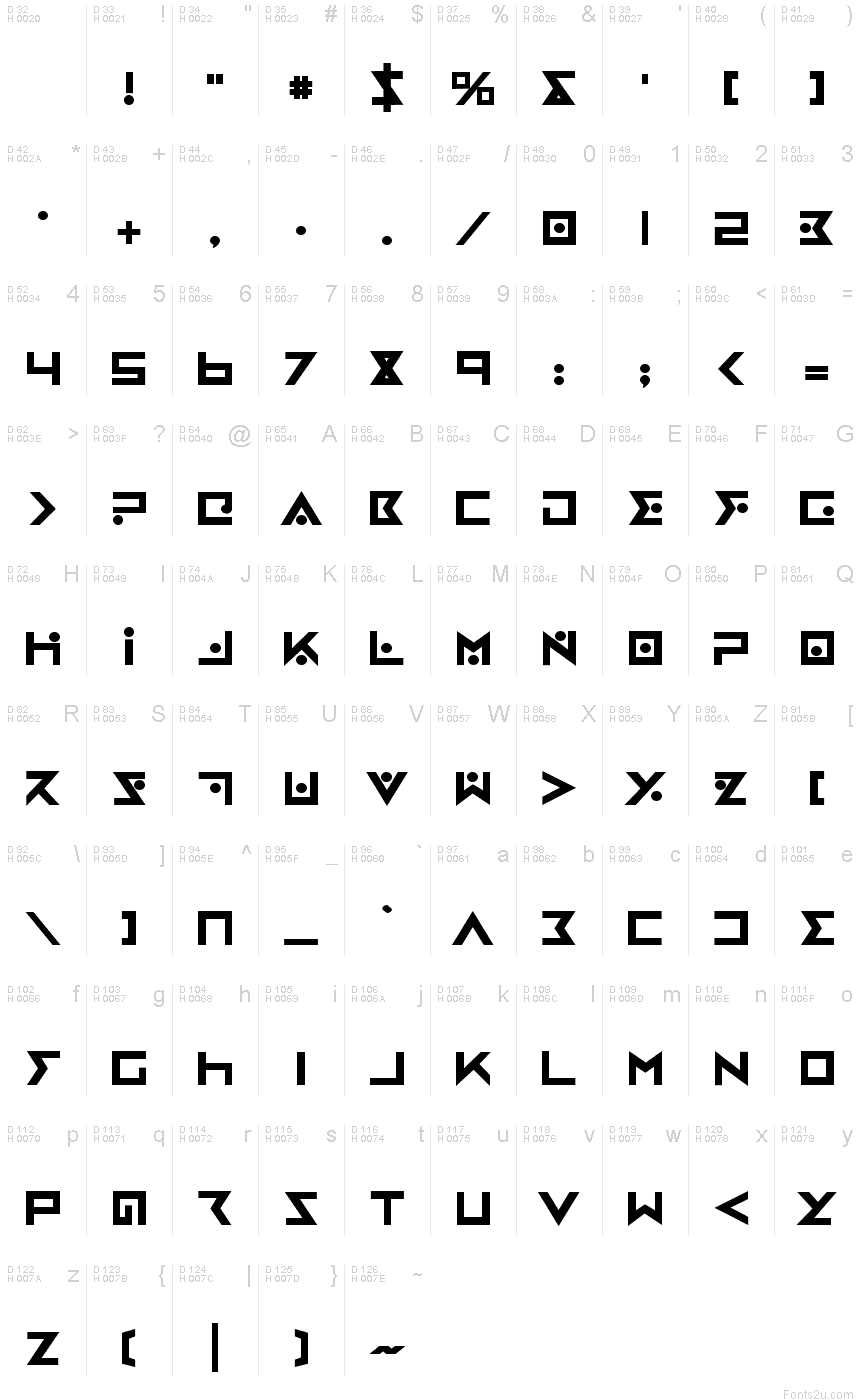
Iron Cobra Bold od Iconian Fonts to darmowy, kanciasty techniczny font typu display z wyraźnym klimatem sci-fi. Litery zbudowane są z masywnych bloków i ostrych skosów, łącząc kwadratowe prześwity z wyciętymi łączeniami, co nadaje projektowi szybki, mechaniczny i niemal emblematyczny charakter.
Sprawdzi się w tytułach plakatów, logotypach gier, ulotkach DJ-skich, brandingu e-sportowym oraz nagłówkach, gdzie krótkie słowa potrzebują syntetycznego, naładowanego energią wyrazu. Jako darmowy font, świetnie nadaje się również do plansz tytułowych i monogramów, ponieważ te kompaktowe, zazębiające się kształty najlepiej prezentują się, gdy pozwolisz przemówić samej geometrii.
Iron Cobra Bold